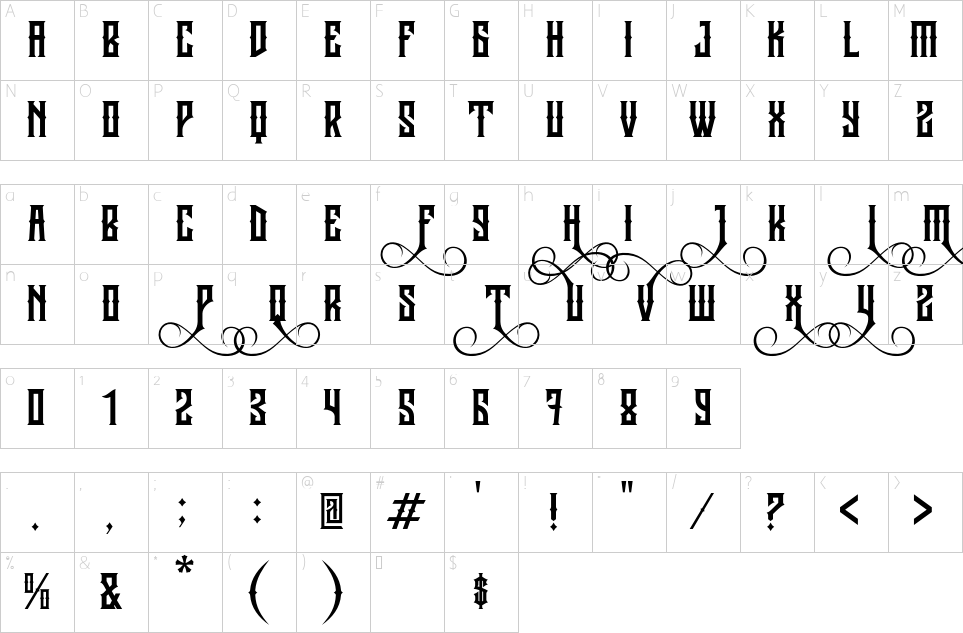
Jibriel Font é uma elegante e versátil escolha para designers gráficos, oferecendo uma mistura sofisticada de linhas clean e detalhes atraentes. Desenvolvida por Mikrojihad Inc, esta fonte vem em versões para Windows e Mac, permitindo que designers de todo o mundo possam experimentá-la em suas próprias plataformas de trabalho. Desde sua criação, Jibriel Font já foi baixada por mais de 25.787 pessoas, um número que reflete o seu valor como uma opção de fonte gratuita excepcional. Seja para criação de design editorial, gráficos de produto ou até mesmo para o design de sites, a Jibriel é uma fonte que não só complementa suas ideias de maneira sofisticada, mas também oferece um amplo leque de opções para personalizar seu projeto de acordo com suas necessidades.